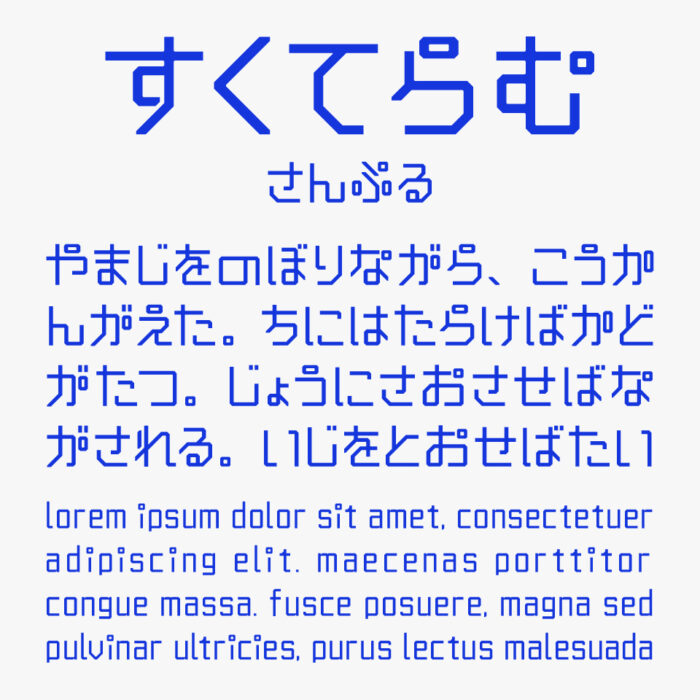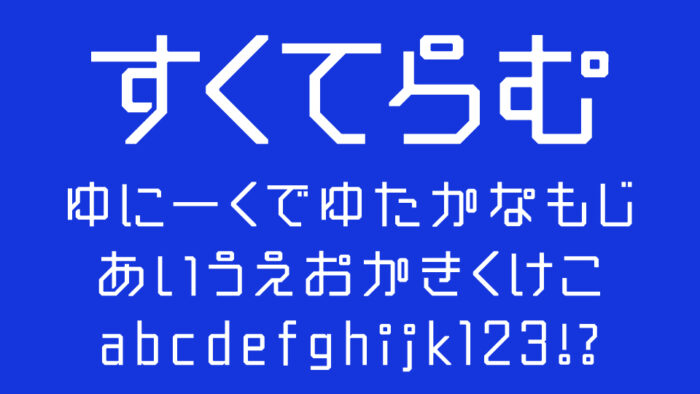
すくてらむフォントは、水平・垂直・斜め45度の直線のみで構成されたデザインフォントです。
角ばったデジタル風の骨格に加えて、緩やかな丸みのある角度が付いていることで、無機質になりすぎない印象になっており、文字ごとのディテールに遊び心を感じるデザインです。
収録文字は、ひらがな・アルファベット・数字・記号(投げ銭ver)が収録されています。
| カタカナ | × |